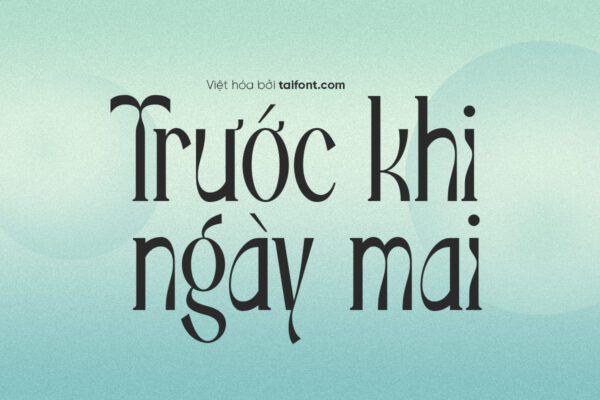
Tên font: Font VIP Vendya Việt Hóa – Font Có Chân Thanh Mảnh Sang Trọng
VIP Vendya là một font serif có chân, nổi bật với phong cách thanh mảnh, nhẹ nhàng nhưng đầy tinh tế. Những đường nét mềm mại kết hợp với chi tiết có chân giúp font mang lại cảm giác sang trọng, quý phái nhưng không kém phần hiện đại.
Phiên bản Việt hóa được xử lý chuẩn chỉnh, hỗ trợ đầy đủ dấu tiếng Việt, giúp font dễ dàng ứng dụng trong các thiết kế cao cấp. Với khí chất thời thượng, VIP Vendya đặc biệt phù hợp cho các thiết kế liên quan đến thời trang, mỹ phẩm, thiệp cưới, hoặc các sản phẩm cần thể hiện sự nữ tính và đẳng cấp.